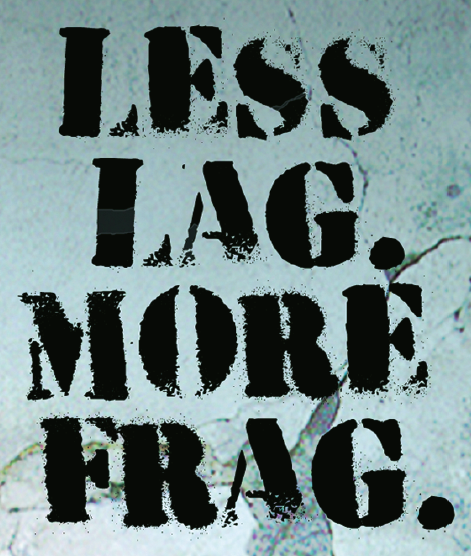
Verwittertes A-Team
Ist das nicht die Stencil STD Bold?
Zumindest die Grundschrift.
Soll das eine Digital-Schrift sein, die modifiziert wurde oder sind das schlecht aufgesprühte Schablonen?
Kann ich anhand des Ausschnitts nicht beurteilen.
Oder habe ich die Frage nicht wirklich verstanden? :?
Hab mich schon bei Da*dingsbums* durch die Eroded-Kategorie gewühlt aber nix gefunden
schau mal in der kategorie „stencil, army“, dort findet sich zb die HVD Peace. ist zwar nicht die gesuchte aber auch gesprüht und schablone.
@ akm:
schau dir die 2 „S“ an: so identisch kann man nicht sprayen, das muss ein font sein! :huhu: